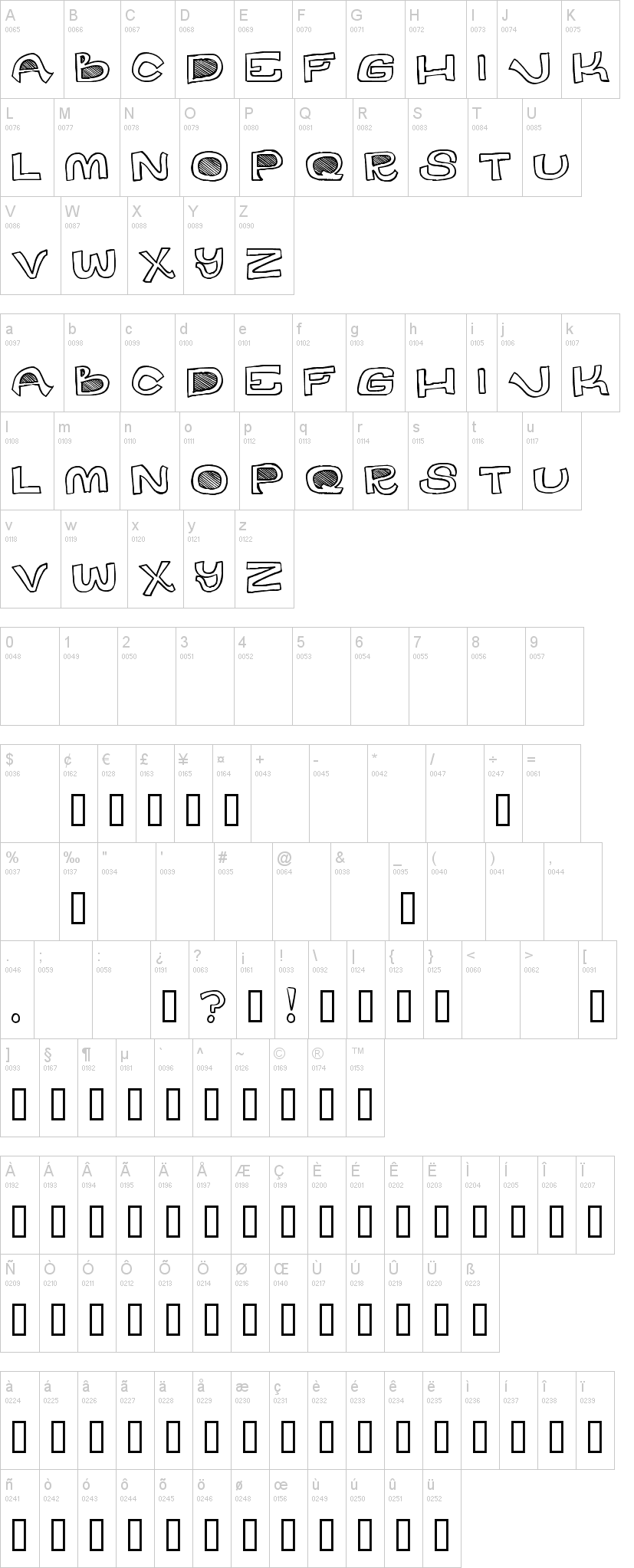
德波特(Des Pot)是一种优雅的手写风格字体,适用于各种设计项目。这种字体具有自然、流畅和高雅的特点,可以用于标志、海报、包装设计、书籍排版等各种场景。 Des Pot 字体家族包括三种不同的字体:Des Pot Regular、Des Pot Bold 和 Des Pot Display。Des Pot Regular 是一种细致、轻盈的字体,适用于正式的场合;Des Pot Bold 是一种更加粗犷、有力的字体,适用于突出重点的场合;Des Pot Display 是一种更加大胆、醒目的字体,适用于标题和重要信息的场合。 Des Pot 字体可以免费下载和使用。如果你想使用一种具有风格、个性的字体来增强你的设计作品,Des Pot 可能是一个不错的选择。内容介绍
Des Pot是一款非常不错的手写艺术字体,具有很好的视觉感,适合于文化类的宣传设计、商业类品牌的广告和产品包装设计以及个性化文字排版等较多场景。